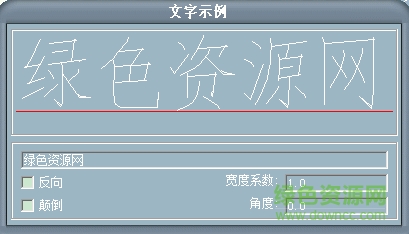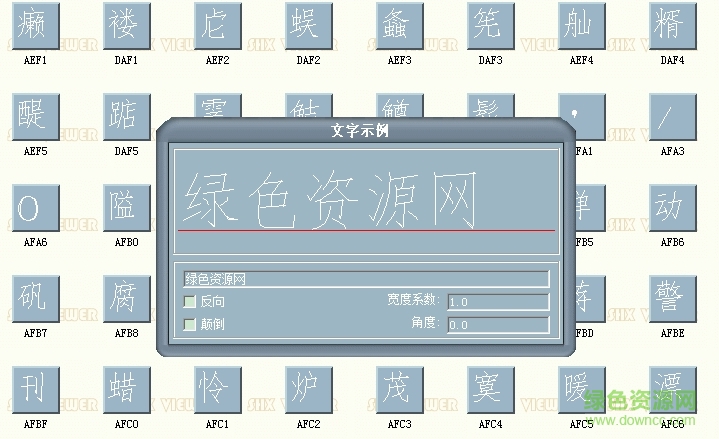
wjgshp.shx字體是autocad軟件中必備的字體文件,這款cad字體主要解決cad圖紙無(wú)法正常顯示等問(wèn)題,需要這款字體的用戶歡迎來(lái)綠色資源網(wǎng)下載。
1、在dwg文件的存儲(chǔ)上占用的空間小,在顯示的速度上比較快。特別是文字比較多的情況下,regen的重顯的速度上的差異更明顯,在實(shí)時(shí)移動(dòng)(pan)的更新上不存在時(shí)差現(xiàn)象。
2、由于Windows字體為外來(lái)字體(相對(duì)于SHX字體),在生成及編輯的過(guò)程中,還不能做到完美無(wú)缺。比如,TrueType字體(Windows字體)的文字在移動(dòng)、拷貝的過(guò)程中,句子的長(zhǎng)度可能與實(shí)際的長(zhǎng)度不同,影響了參考定位。再如,TrueType字體的實(shí)際高度可能與指定的高度之間有差異,不能精確地指定字高,只能通過(guò)試錯(cuò)的方式確定,影響了繪圖的速度,也影響了編程控制的難度。
3、由于SHX字體為線型字體,可以像線段一樣指定特別屬性,產(chǎn)生特殊效果。比如,可以指定厚度值,從而產(chǎn)生立體效果。
4、與TrueType字體相比,SHX字體美觀效果不夠理想,但在工程中尚可滿足需要。SHX字體相當(dāng)于硬筆書(shū)法,在模擬毛筆書(shū)法上存有差距。